慢慢喜欢你是一款富有青少年气息的创意字体。笔画交接处有爱心的形状,笔画中的点画与撇形成三角形的对比,灵动可爱。字形轮廓整体统一,具有一定的易读性,慢慢喜欢你字体的个性乖巧灵活,清新萌动。
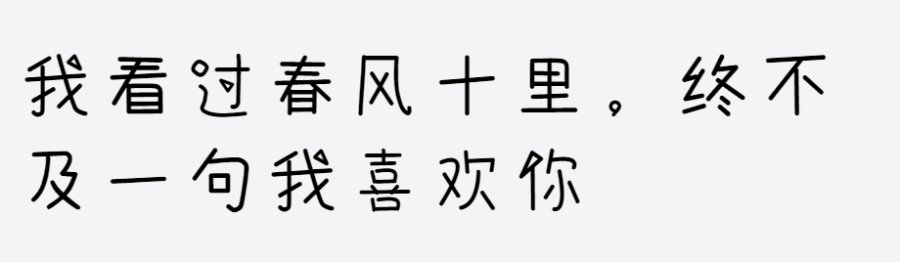
你是戒不掉的喜欢是一款非常漂亮的中文字体,同时也是由文道字库倾情发布的作品,字体的菱角进行过专业的处理,显得是十分圆滑,更融入了爱心符号,整体显得更加的可爱。
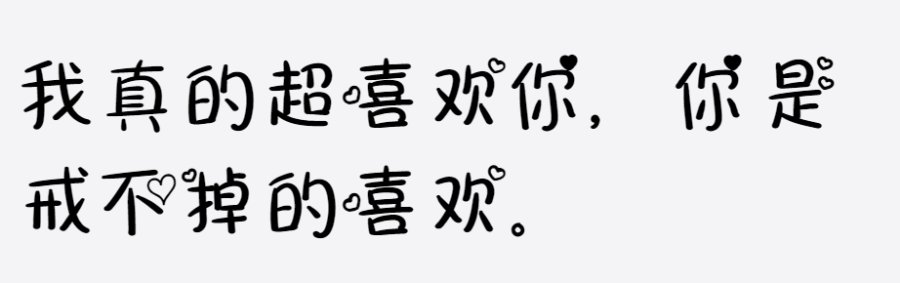
我们不用纠结我们的出场相遇方式,不用说谈恋爱一定要轰轰烈烈,也不用在意谁先主动,但是就是想和你有谈个恋爱,一场不分手的甜蜜恋爱。有个恋爱和你谈字体是义启字库推出的一款个性艺术字体,自带爱心装饰效果,非常有意思。很适合在情人节表白时候使用,为你的表白加分。